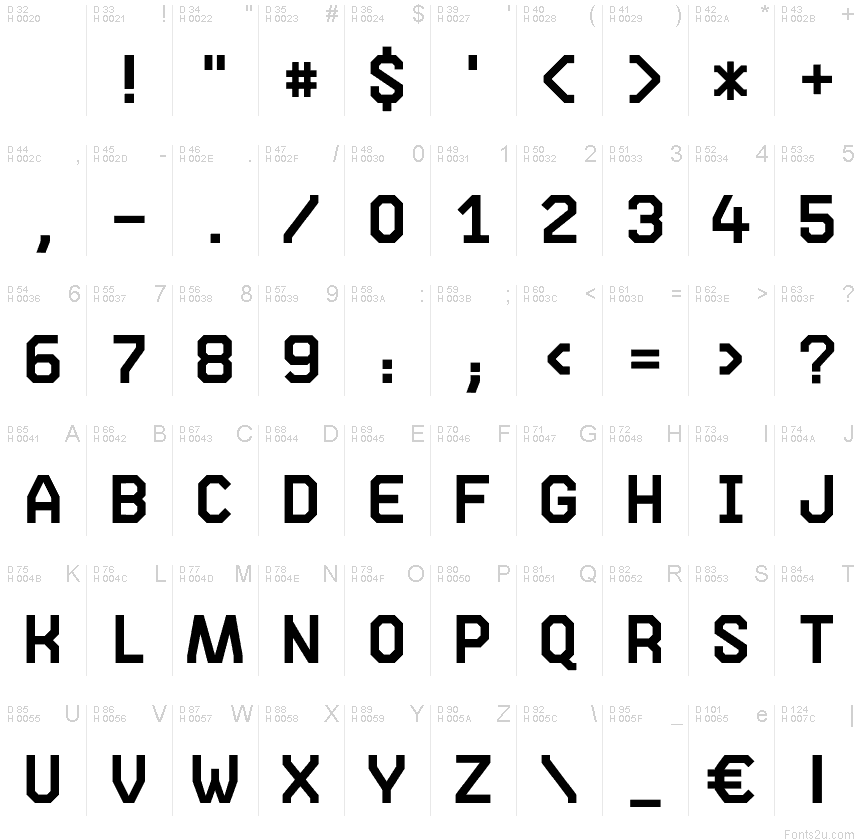
Phase 05 autorstwa Svena Tobiasa Kilsa to darmowy krój techno typu display o ostrym, cyfrowym charakterze w stylu old-school. Litery bazują na masywnej geometrii, ściętych narożnikach i heksagonalnych skrętach, które sprawiają, że alfabet wygląda bardziej na zaprojektowany niż narysowany, przywodząc na myśl kompaktowy klimat ery automatów arcade.
Świetnie sprawdza się w brandingu gier, ulotkach muzyki elektronicznej, plakatach sci-fi, kartach tytułowych i opakowaniach, które wymagają syntetycznego pulsu lat 80. Jako darmowy font, najlepiej działa w krótkich nagłówkach, logotypach i etykietach przypominających interfejsy, gdzie te wycięte kąty i surowe kształty mówią same za siebie bez potrzeby używania dużej ilości tekstu.